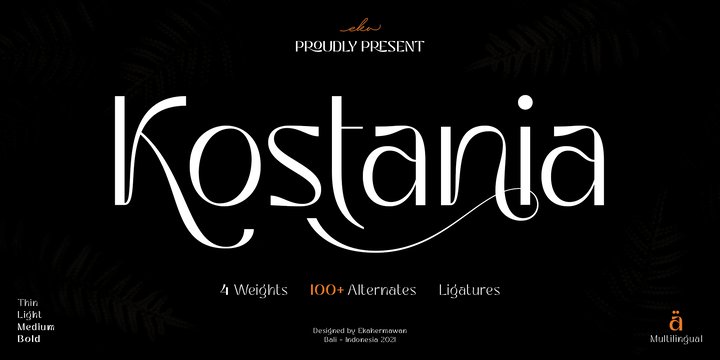
[Myfonts] Kostania Font
Kostania - это элегантный и уникальный шрифт для любого использования на дисплее с 4 вариантами начертания от тонкого до полужирного.
Kostania включает в себя множество альтернативных и лигатурных символов, которые позволят вам получить разнообразные результаты типографического дизайна.
Kostania - это универсальный шрифт для многих дизайнерских проектов, таких как дизайн логотипов, брендинг, плакаты, журналы, этикетки, товары, приглашения, презентации, реклама и многое другое!